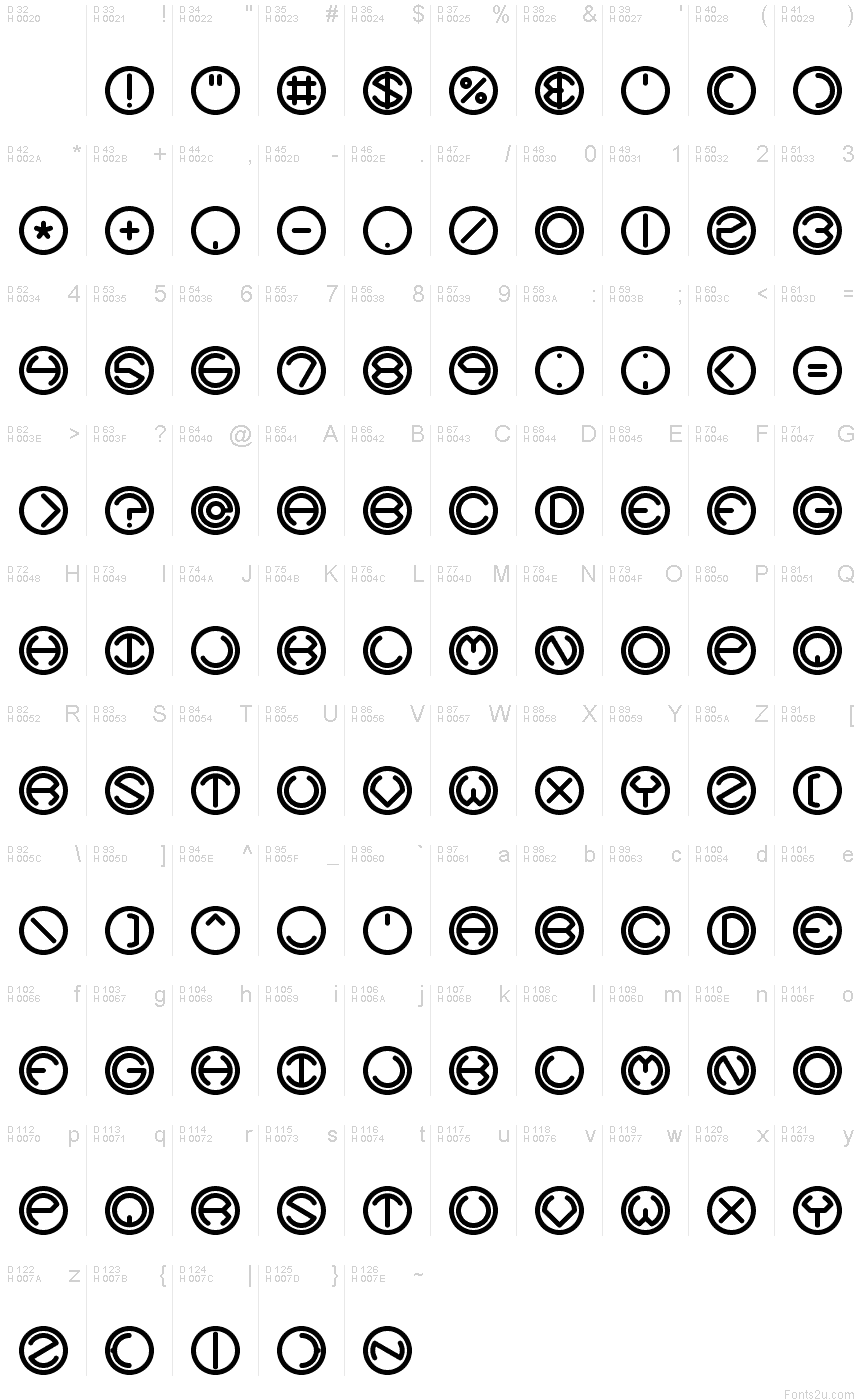
Spheroids di AEnigma Fonts è un font display retro-futurista gratuito, costruito con forme circolari che ricordano piccoli emblemi. Le lettere ruotano attorno a un'idea precisa: anelli esterni pesanti, tratti geometrici fluidi e aperture troncate che rendono il font simile alla segnaletica di una vecchia mostra scientifica o alla confezione di un giocattolo dell'era spaziale.
Funziona alla grande ovunque serva un titolo con quel look «chiuso in una sfera»: volantini arcade, poster sci-fi, copertine di album, bozze di loghi e brevi linee di branding. Essendo un font gratuito, dà il meglio di sé in contesti di display breve, specialmente in titoli o monogrammi, dove queste forme racchiuse e le silhouette tondeggianti comunicano subito l'atmosfera.
Spheroids BRK — Presentazione del carattere
Spheroids BRK